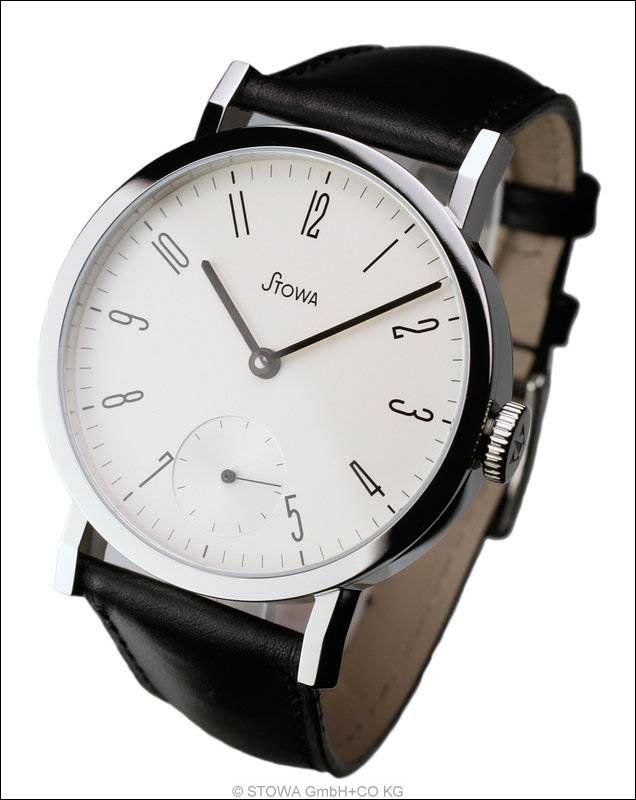
Zifferblattschriftart auf Stowa
könnt ihr mir bitte sagen, welche Schriftart die Ziffern haben?
Vielen Dank für die Antwort! In der Tat hilft mir das wirklich schon sehr viel weiter! Da fehlen nur die Asymmetrie (Nord-Süd, oder wie man das nennen soll) und die kleinen Häkchen, aber das ist nicht so schlimm. Möglicherweise kann man die Fonts ja sogar noch bearbeiten, muss mal sehen. :)